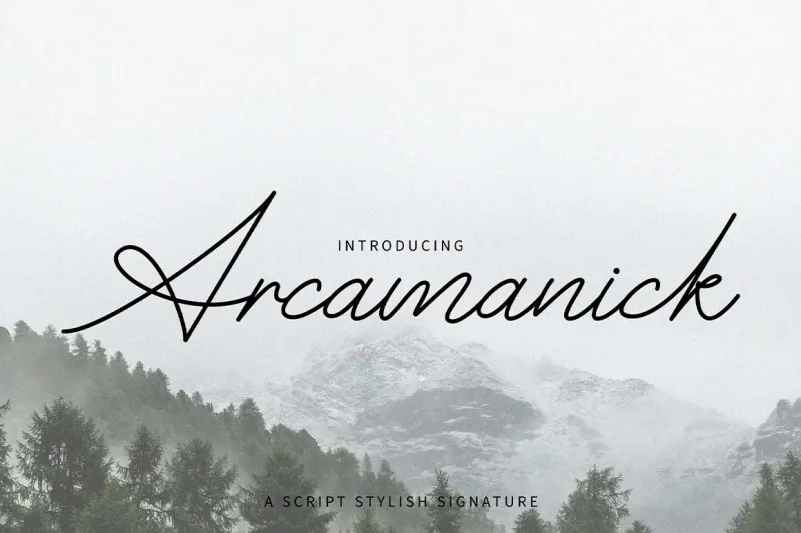
Arcamanick Font – Download Grátis
A Arcamanick Font é uma tipografia casual para assinaturas, ideal para aqueles buscando algo divertido e fácil de usar sem perder a elegância e a seriedade necessárias em projetos profissionais. Com traços monolineares e um estilo deslizante e descontraído, esta fonte oferece uma aparição fresca e amigável que pode ser usada com precisão para branding e criação de logotipos, design para casamentos, postagens nas redes sociais, anúncios, embalagem de produtos, designs de produto, etiquetas, fotografia ou mesmo como um toque de identidade visual em uma série de projetos. Sua simplicidade e alegria garantem que esteja sempre pronto para entrar em qualquer projeto que exija o sabor do traço humano. E como se não bastasse, ela também é perfeita para criação de convites, materiais de escritório e qualquer outro tipo de trabalho que precise de um toque único e divertido. Com a Arcamanick Font, você pode transformar suas ideias em algo ainda mais especial e original.